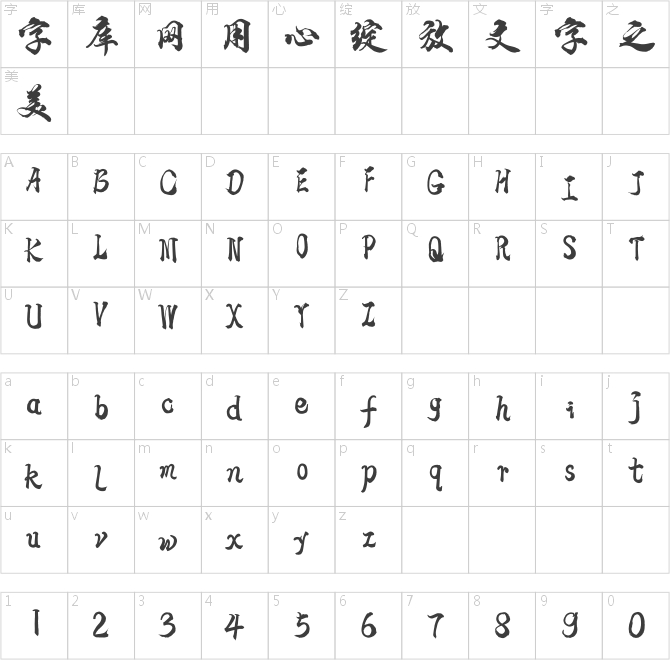
字體名稱: 段寧毛筆行藝體
段寧毛筆行藝體
段寧毛筆行藝體介紹
段寧毛筆行藝體含9663個漢字和必備的其他字符,由書法家段寧老師手寫原稿并親自制作完成的一套字庫,是一套真正的漢字大字庫。有簡體字、繁體字、生僻字,你所要的字這里都有。這套字最大的亮點是,字體氣勢磅礴,遒勁有力,有漢字的規范結體又有藝術的元素,同時還保留了毛筆的飛白和游絲,基本上與毛筆寫在宣紙上一樣的效果。這款大字庫適合影視、網頁、包裝、印刷等各類廣告媒體使用。 非商用免費,商用必須聯系版權人段寧購買授權,電話/微信 15851552102